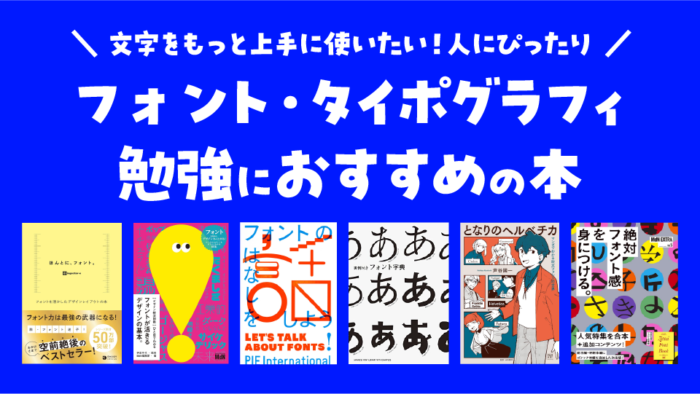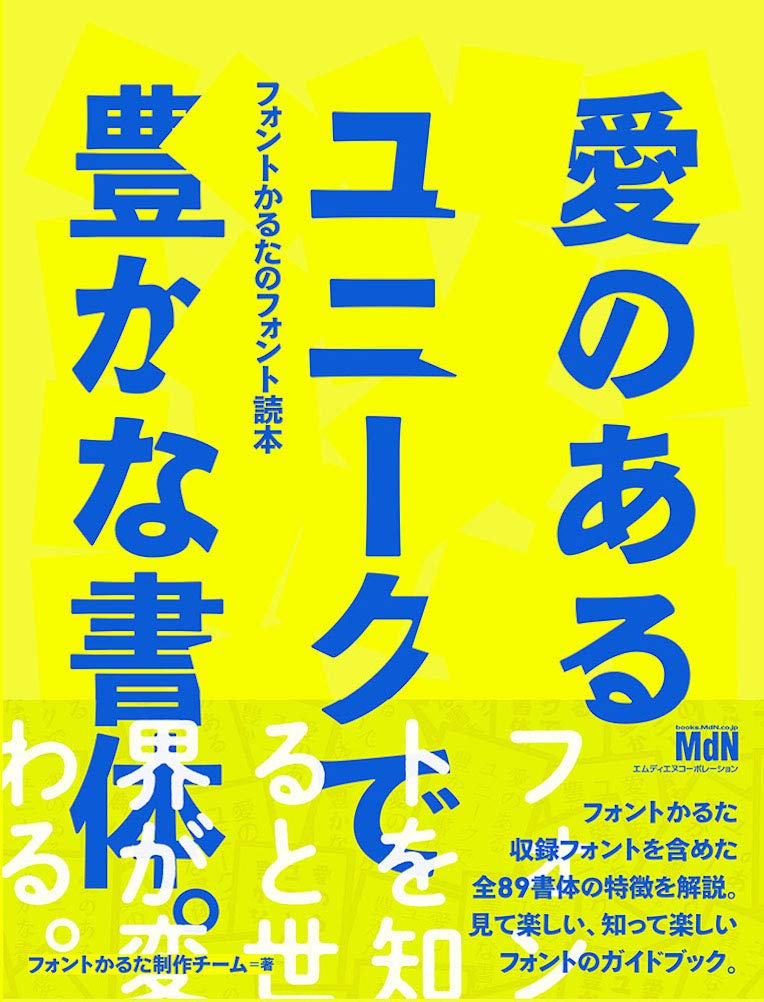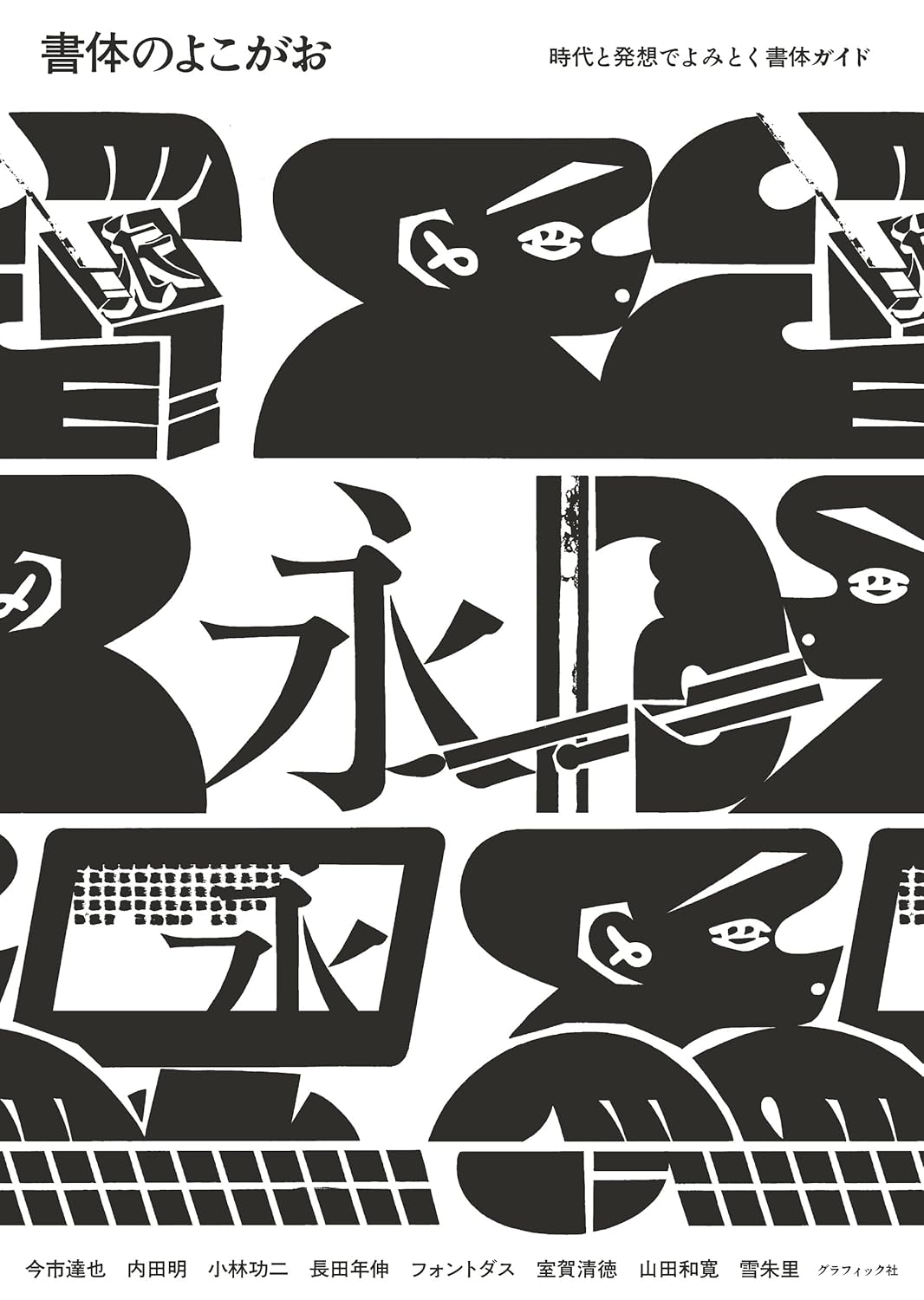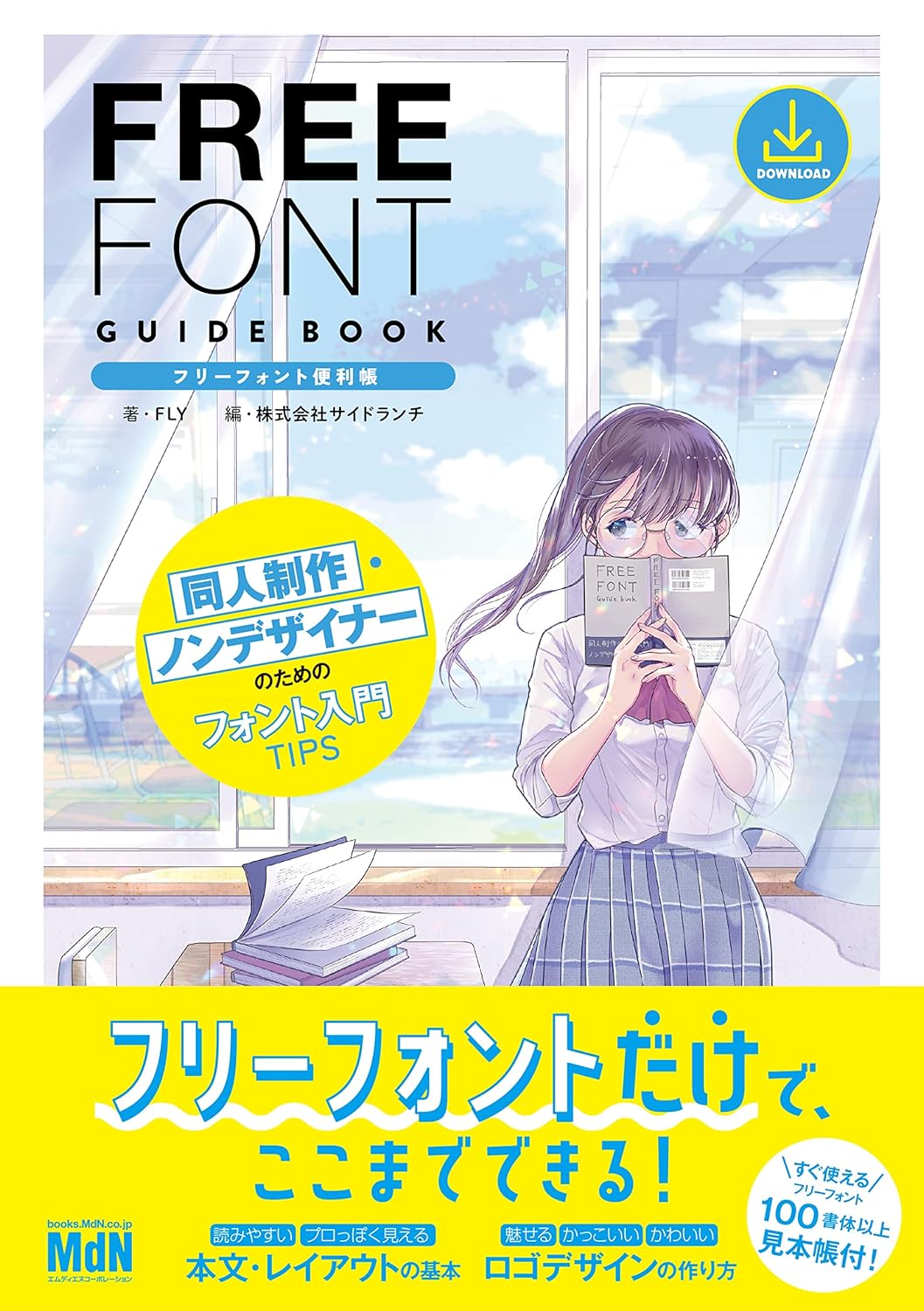
フォント・書体・タイポグラフィの勉強におすすめの本
デザインをしていると、フォント選びや文字組みで悩むことってありますよね。「どのフォントを使えばいいんだろう」「もっとセンスよく見せたい」そんな時に頼りになるのが、実践的なフォント本です。
フォントをうまく活用したい方、デザインを勉強中の方など初心者の方でも読みやすく、すぐに実践で使えるものばかりを集めました。
フォント・書体・タイポグラフィの学習におすすめの本
ほんとに、フォント。フォントを活かしたデザインレイアウトの本(ingectar-e 著)
ベストセラー『けっきょく、よはく。』の著者が手がけたフォント解説書です。
カフェのメニューやポスターなど、身近なデザイン実例が豊富で、「これはNG」「これならOK」という比較が分かりやすいんです。感覚的にフォント選びのコツをつかめるので、デザイン初心者の最初の一冊としてもおすすめです。
[デザイン技法図鑑]ひと目でわかるフォントが活きるデザインの基本。(伊達千代 監修/MdN編集部 編)
図解が充実していて、パラパラめくるだけでも勉強になる一冊。
印象別のフォント使い分けや文字組み、余白の取り方まで、体系的にまとめられています。「こういう雰囲気を出したい時は、このフォント」というように、目的に合わせて引けるので、手元に置いておくと便利です。
見てわかる、迷わず決まるフォントのアイデア マネするだけでセンスのいいフォント(ingectar-e 著)
「いつも同じフォントばかり使ってしまう…」という方に特におすすめ。
メイン・アクセント・ベースという3つの役割ごとに、相性のいいフォントの組み合わせを紹介しています。掲載例をそのまま参考にするだけで、グッとデザインが洗練されますよ。
フォントの話をしよう(パイ インターナショナル 編著)
プロのグラフィックデザイナーやフォントメーカーなど、19組へのインタビュー集です。
「なぜこのフォントを選んだのか」「オリジナル書体はどうやって作るのか」など、現場のリアルな声が聞けるのが魅力。読み物として面白く、フォントへの理解が深まります。
タイポグラフィの基本ルール プロに学ぶ、一生枯れない永久不滅テクニック(大崎善治 著)
タイトル通り、一生使える基本が詰まった本です。文字や組版の基礎から、9つのレイアウトパターン、演出テクニックまで丁寧に解説されています。
「デザインの良し悪しはタイポグラフィで決まる」という著者の言葉が印象的で、基礎をしっかり固めたい方にぴったりです。
レタースペーシング タイポグラフィにおける文字間調整の考え方(今市達也 著)
文字間の調整だけに特化した、ちょっとマニアックな本。
でも、ロゴやタイトルを作る時に「なんか詰まって見える」「バランスが悪い」と感じたことがある方には、目からウロコの内容です。感覚ではなく、理論的にスペーシングを考える方法が学べます。
[改訂版]実例付きフォント字典(パイ インターナショナル)
国内26社、約2,500種類もの和文書体を掲載した、まさに「字典」。
広告や書籍、パッケージなど、実際の使用例も載っているので、「このイメージにはどのフォント?」と迷った時にサッと引けます。デザイナーなら手元に置いておきたい一冊です。
フリーフォント便利帳 同人制作・ノンデザイナーのためのフォント入門TIPS(FLY 著/サイドランチ 編)
同人誌や小説、漫画を作る方向けのフォント本です。100種類以上の無料フォントを紹介していて、インストール方法からライセンスの確認まで、初心者に優しい内容になっています。「まずは無料フォントから試したい」という方におすすめです。
Webフォント実践ガイド Google Fontsではじめる 美しく機能的なタイポグラフィ(飯塚修平 著)
Web制作に関わる方なら、この本は要チェック。Google Fontsの使い方やWebフォントの基礎、実装方法まで幅広くカバーしています。
紙のデザインとは違ったWebならではのフォント活用法が学べるので、Webデザイナーやエンジニアの方にもおすすめです。
となりのヘルベチカ マンガでわかる欧文フォントの世界(芦谷國一 作/山本政幸 監修)
欧文フォントを擬人化したマンガ形式の入門書。HelveticaやFuturaなどの有名書体が、キャラクターとして登場します。
堅苦しい専門書は苦手…という方でも、物語を楽しみながらフォントの個性や歴史が学べるユニークな一冊です。
MdN EXTRA Vol.5 絶対フォント感を身につける。(エムディエヌコーポレーション 編)
デザイン誌「MdN」の人気特集をまとめたムックです。「絶対フォント感」って面白いネーミングですよね。これは、街で見かけた書体を見ただけで「あ、これは○○体だ!」と言い当てられる能力のこと。
明朝体やゴシック体の歴史、それぞれの特徴、タイプデザイナーへのインタビューなど、読み応えのある内容が詰まっています。何より嬉しいのが、付録のフォント見本帳。650書体以上が収録されているので、「あのお店の看板、何のフォントだろう?」と気になった時にすぐ調べられます。フォント好きにはたまらない一冊です。
欧文書体 基礎知識と使い方(小林章 著)
欧文フォントといえば、この本。世界的なタイプデザイナー・小林章さんが書かれた『欧文書体』と『欧文書体2』を合本して、最新情報にアップデートした改訂版です。
ローマン体やサンセリフ体の定番書体はもちろん、イタリックの使い方、記号の扱い方、目的に合わせた書体の選び方まで、欧文書体のことならこれ一冊でOK。全ページカラーで見やすく、辞書代わりに手元に置いておくと、何かと重宝します。「欧文フォントって難しそう…」という方こそ、読んでみてほしいです。
愛のあるユニークで豊かな書体。フォントかるたのフォント読本(フォントかるた制作チーム 著)
タイトルからして素敵なこの本、実は「フォントかるた」という遊びながら学べるカードゲームから生まれた書籍なのです。かるたに収録された48書体を含む、計89書体をじっくり解説しています。
面白いのが、テレビのテロップやポスター、道路標識など、私たちが毎日目にしている文字を例に挙げているところ。「あ、あのテレビ番組で見たやつだ!」「この標識の文字ってそういう書体だったんだ!」と、身近な発見がたくさんあります。
各書体の歴史や特徴、どんな場面で使われているかが分かりやすく書かれていて、巻末には書体見本もずらり。ページをめくるだけでワクワクする、眺めているだけでも楽しめる一冊です。フォントを「勉強」というより「遊び」として楽しみたい方にぴったりです。